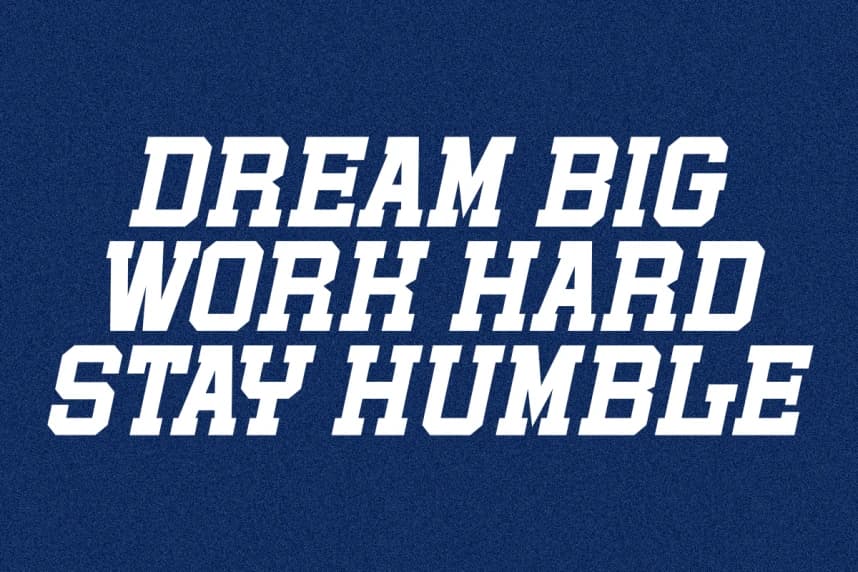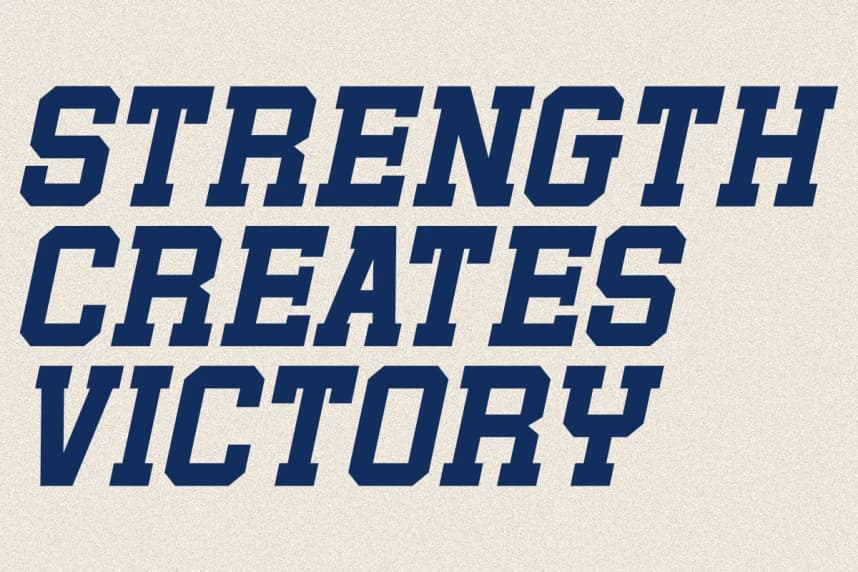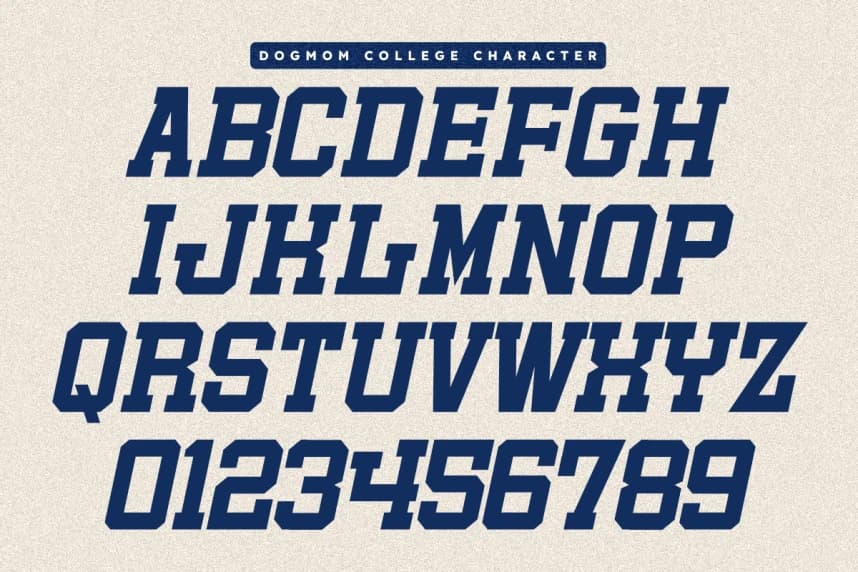
Dogmom College Font
Dogmom College Font, modern yaratıcı projelerinize klasik bir varsity estetiği kazandırmak üzere tasarlanmış cesur ve güçlü bir kolej gösterim yazı tipidir. İtalik stil ile. Bu yazı tipi, üniversite sporlarının ve takım ruhunun zamansız ruhunu yansıtır.
Dogmom College Font, modern yaratıcı projelerinize klasik bir varsity estetiği katmak için tasarlanmış cesur ve güçlü bir kolej gösteri yazı tipidir. İtalik Stil ile. Bu yazı tipi, üniversite sporlarının ve takım ruhunun zamansız ruhunu yansıtır.